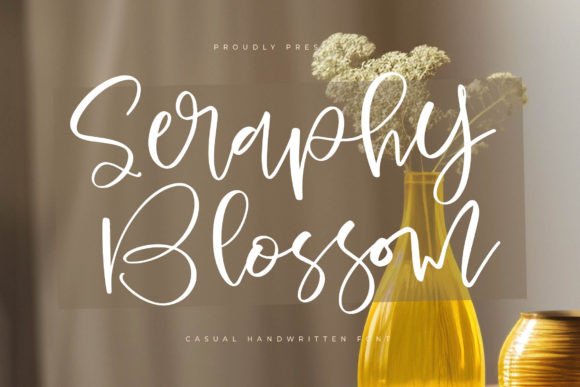
Seraphy Blossom
Якщо ви шукаєте високоякісні ресурси, такі як Seraphy Blossom, цей преміум-пакет є фантастичним вибором для ваших творчих проектів.
Незалежно від того, чи створюєте ви продукти POD (друк на вимогу), весільні запрошення або графіку для соціальних мереж, Seraphy Blossom стане ідеальним вибором.